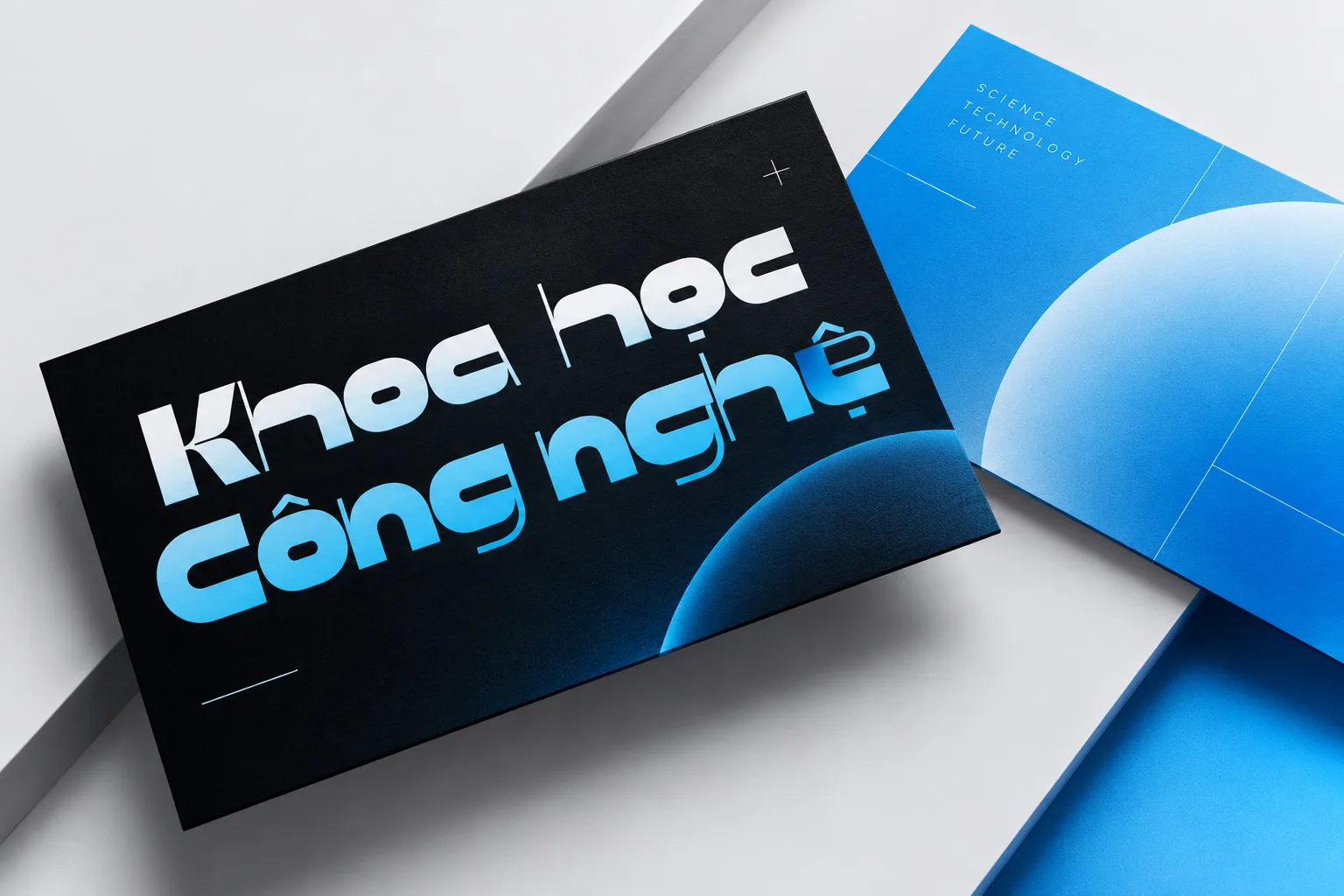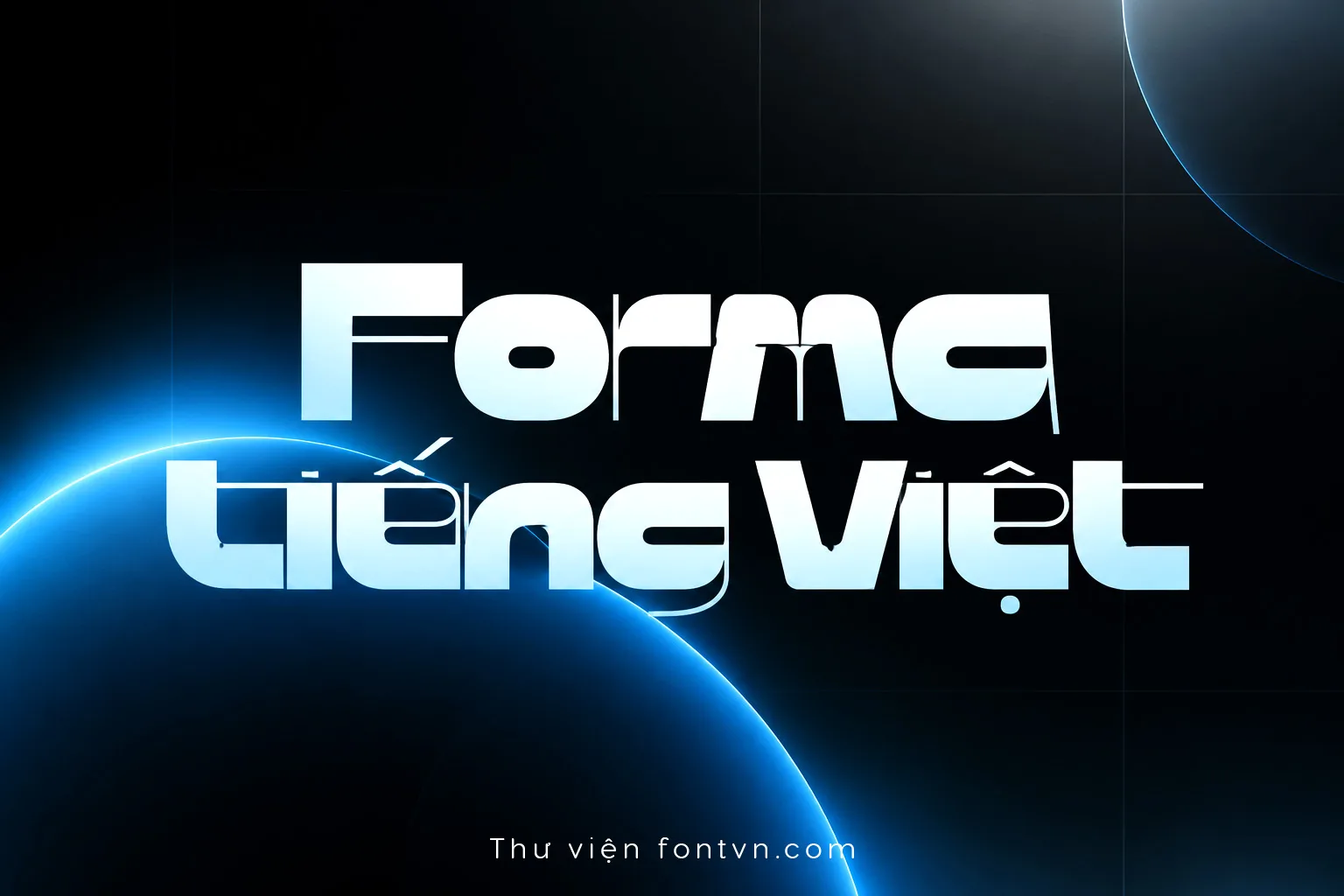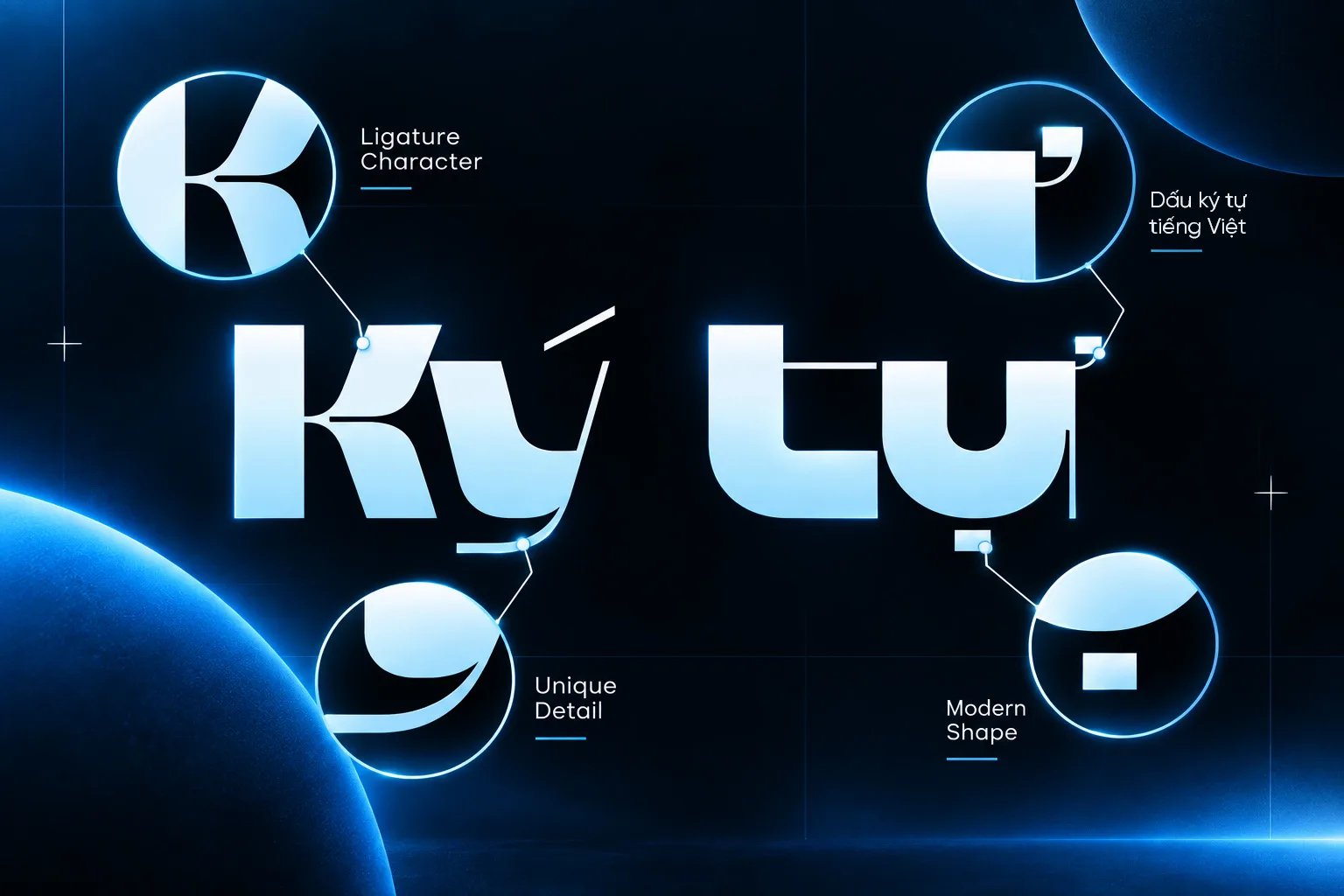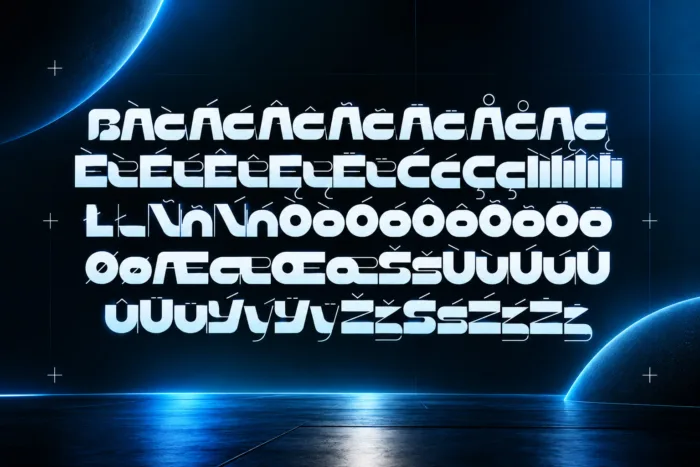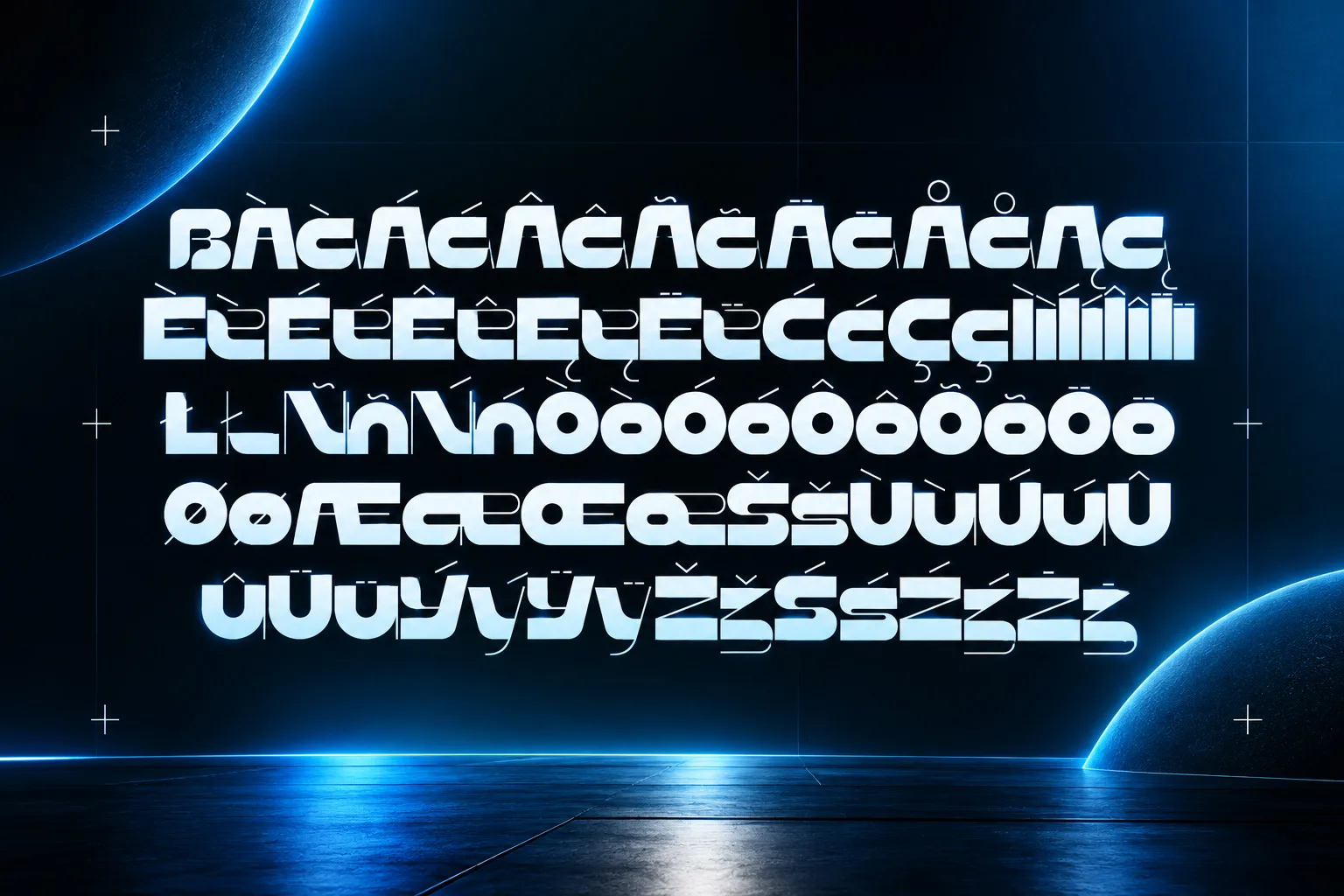
DVN Forma tiếng Việt – Font Display Hình Học Hiện Đại, Futuristic & Cá Tính
DVN Forma là một kiểu chữ Display Sans Serif mang tinh thần hình học, hiện đại và futuristic, nổi bật với những đường nét bo tròn, tỷ lệ chữ rộng cùng các chi tiết cắt ngang đầy cá tính.
Thiết kế của DVN Forma tạo cảm giác mạnh mẽ nhưng mềm mại, kết hợp giữa hình học tối giản và những biến tấu độc đáo trên từng ký tự. Các nét chữ được xử lý đặc biệt giúp font nổi bật ngay cả khi sử dụng ở kích thước lớn, rất phù hợp cho những thiết kế cần tạo ấn tượng thị giác mạnh.
Phiên bản DVN Forma Việt Hóa được xử lý đầy đủ hệ thống ký tự tiếng Việt, giúp font có thể sử dụng thuận tiện trong thiết kế tại Việt Nam.